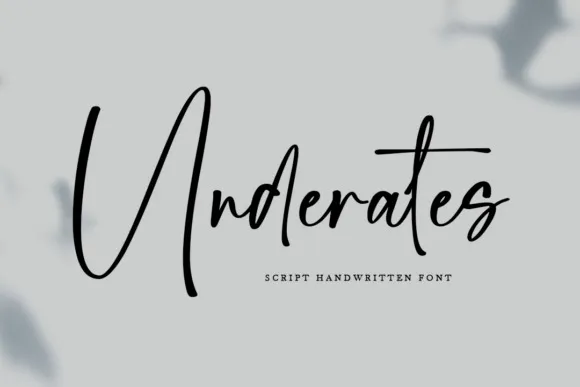
A Underates Font é uma elegante solução criada por Moove Studio que traz um toque delicado e autêntico à sua designação. Esta fórmula script, disponível para todos os projetos de design, é perfeita para adicionar um ar descontraído e romântico ao seu trabalho. Com suas linhas suaves e detalhes doces, essa fonte vai fazer a diferença em qualquer projeto que você estiver trabalhando — seja uma identidade visual única ou uma carta personalizada. Com sua disposição fluida e personalizável, a Underates Font é um grande complemento para todos os tipos de design. Ela tem o potencial de dar uma sensação encantada a seus projetos e certamente vai tornar seu trabalho mais amigável e receptivo aos olhos do consumidor. Seja você designer de logotipos, criativo ou web, essa fonte é uma ferramenta valiosa para fazer sua marca mais vívida e única. Não perca a chance de trazer um toque especial a seus projetos com essa fórmula delicada mas poderosa. Descubra por si mesmo como ela pode transformar seu design!